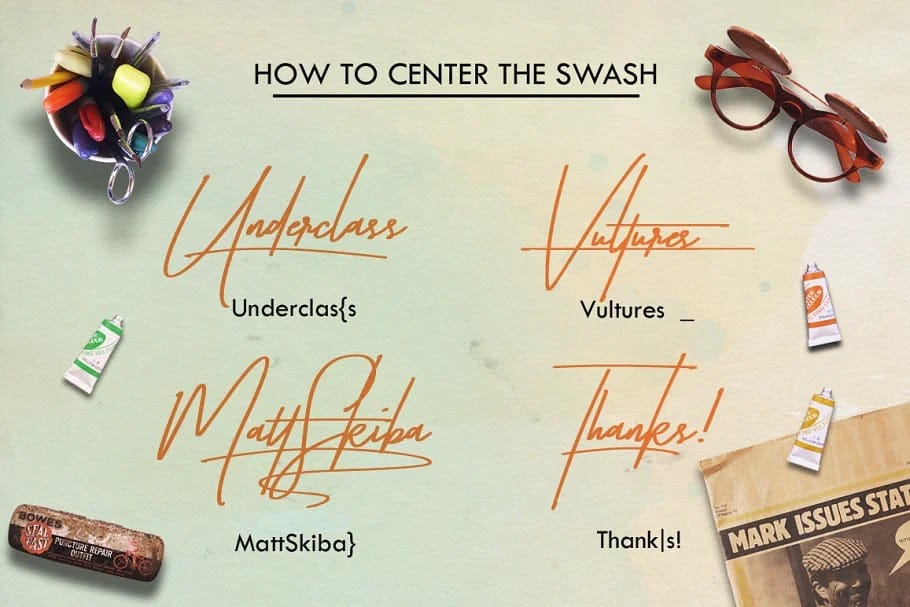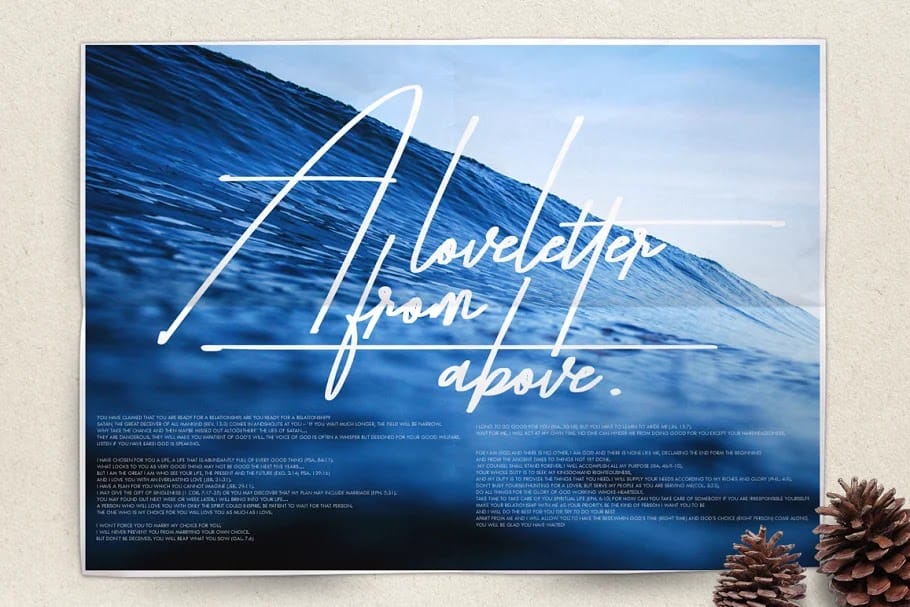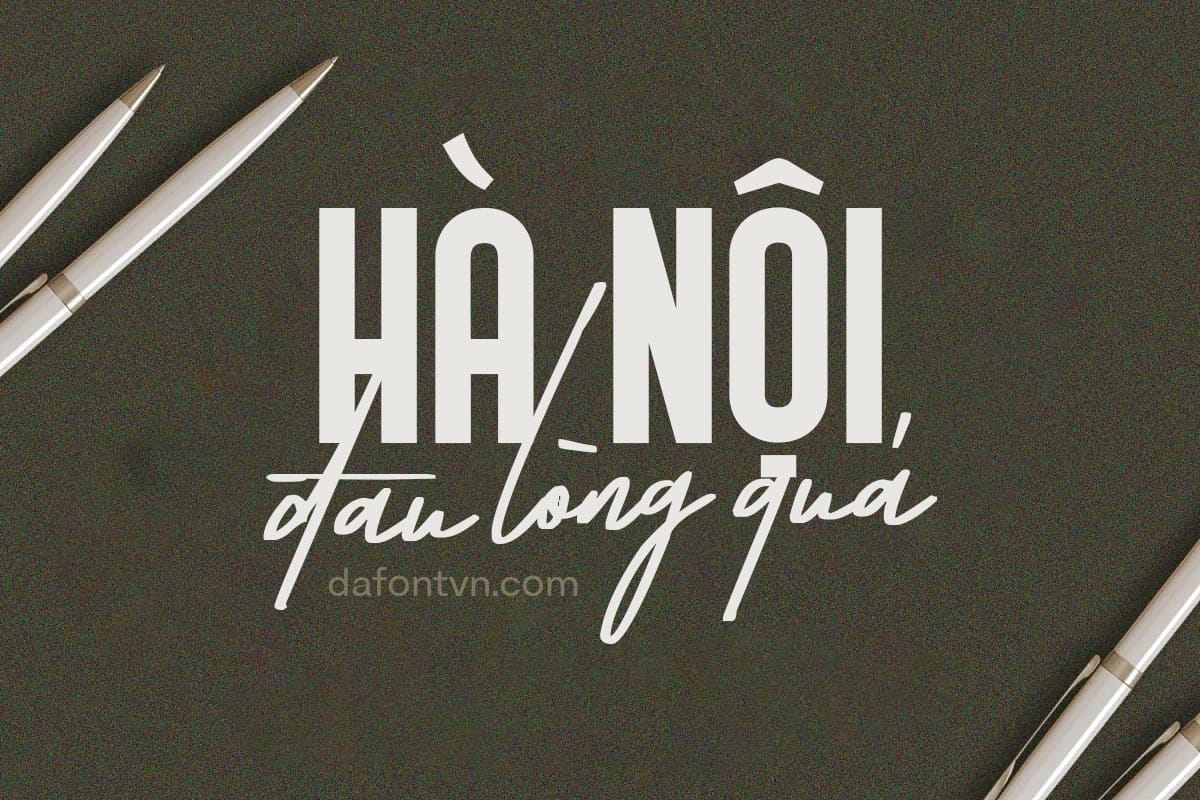
Taken by Vultures một kiểu font chữ viết tay ấn tượng, sự pha trộn của glyph mang lại sự độc đáo nhất và một cảm giác tự nhiên như được viết bằng tay. Font chữ thích hợp sử dụng làm văn bản chữ ký hoặc cho hầu hết các thiết kế của bạn.
Font Taken by Vultures Việt Hóa đầy đủ, kerning và tối ưu hóa lại cho máy tính và điện thoại để sử dụng nhanh hơn. Việt hóa bởi SVN.